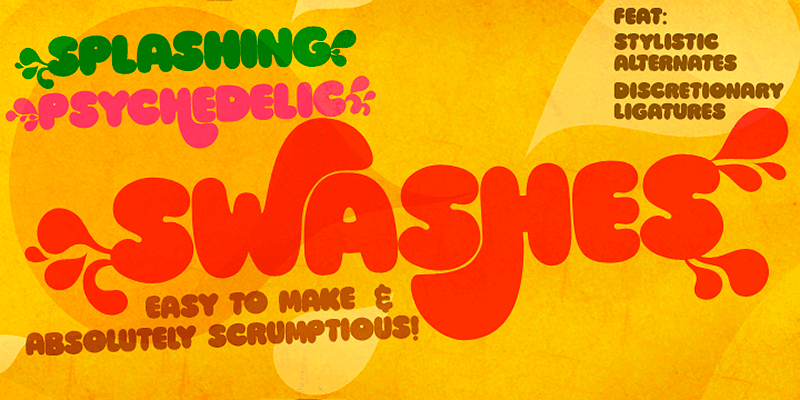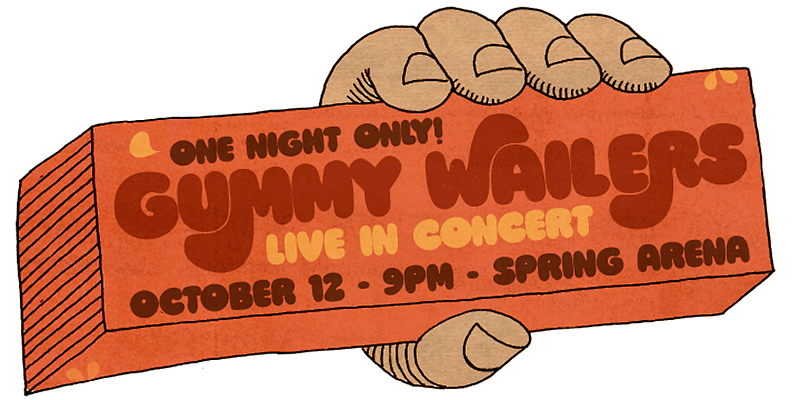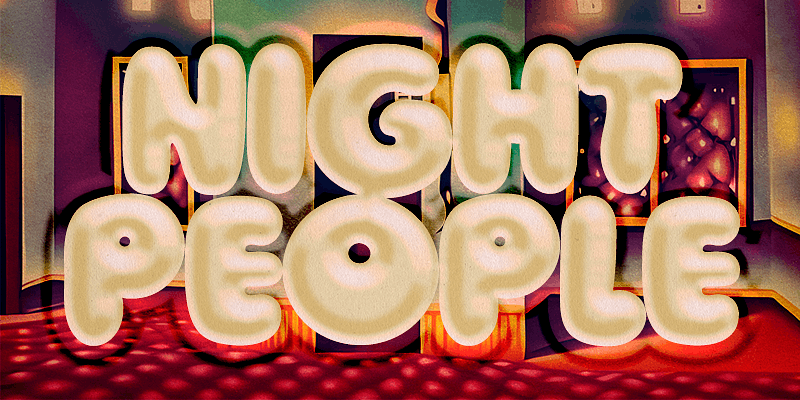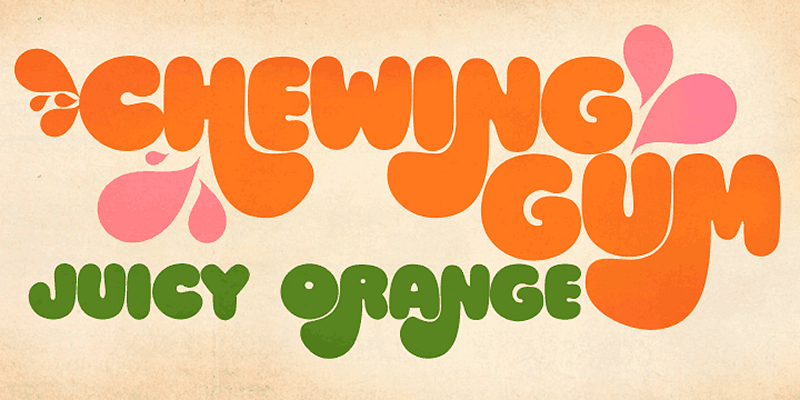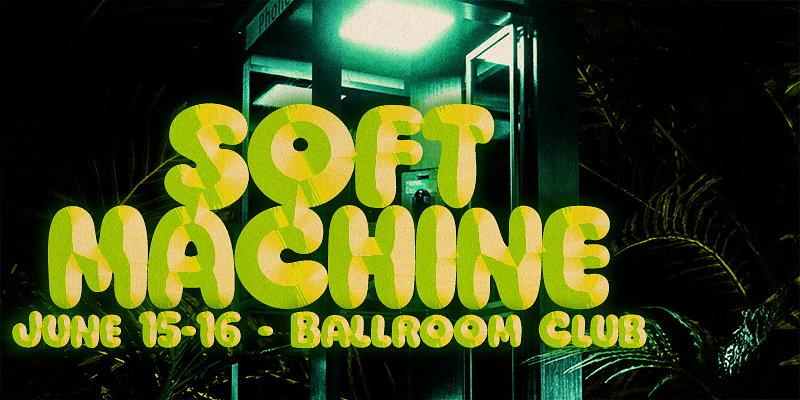
PintassilgoPrints ist ein digitaler Schriftanbieter mit Sitz in Brasilien, der 2009 von Erica Jung & Ricardo Marcin gegründet wurde. PintassilgoPrints ist bekannt für die nachweislich vielseitige und künstlerische Auswahl an Schriften, die sich jeweils durch einen eigenen Stil und kreatives Flair auszeichnen. Schreibschriften für Einladungen! Serifenschriften für Schlagzeilen! Serifenlose Schriften für Poster! Vintage- und Retro-Schriften, skurrile und verspielte Schriften, durch Handschriften und Kalligrafie inspirierte Schriften – die Möglichkeiten für Kreative und Designer, ihrer Arbeit auf originelle Weise Ausdruck zu verleihen, sind endlos.